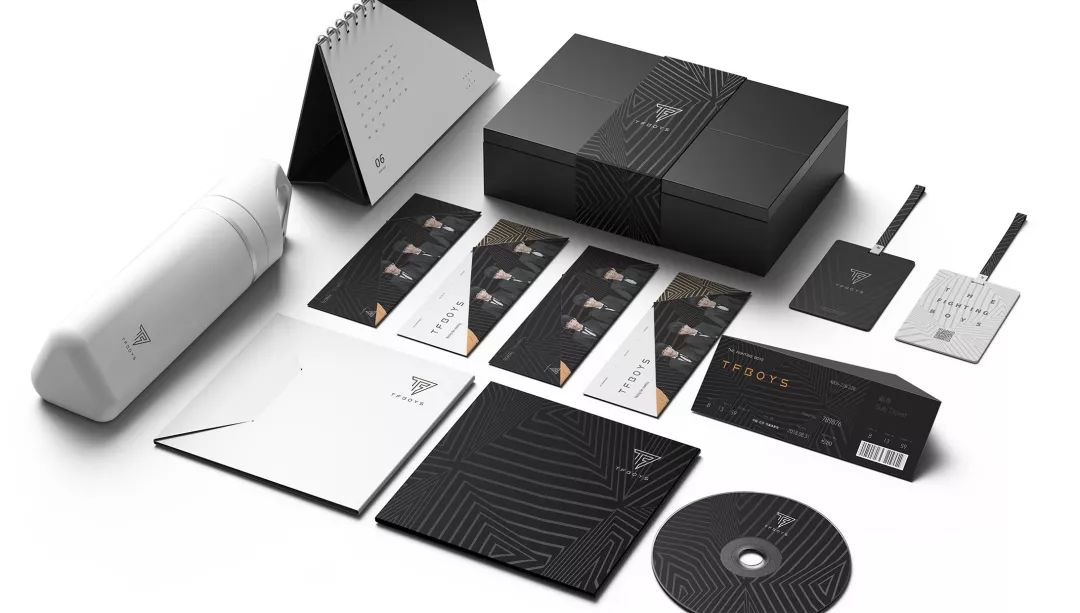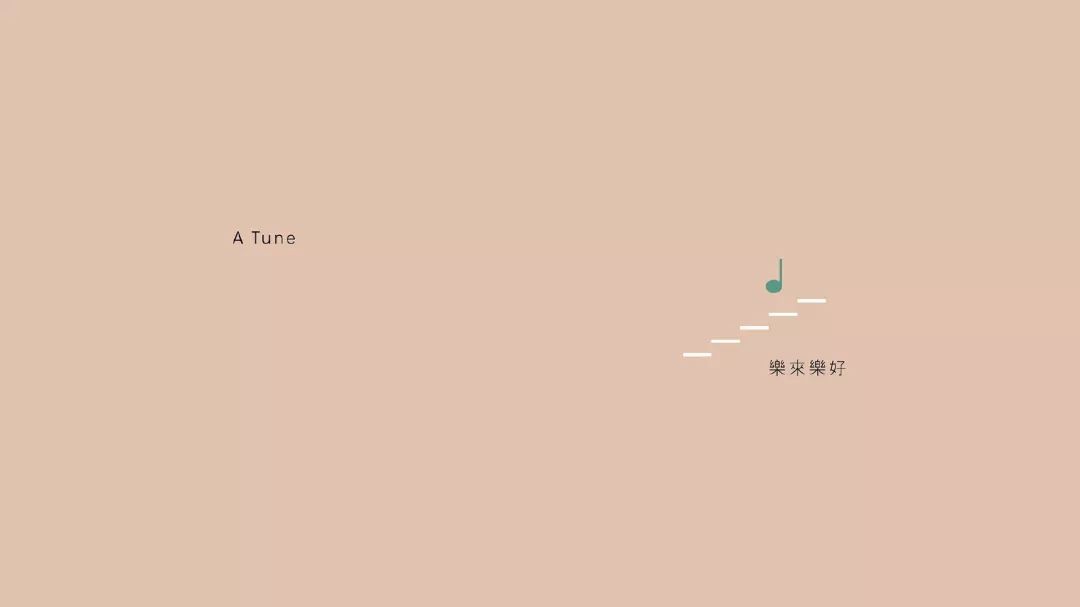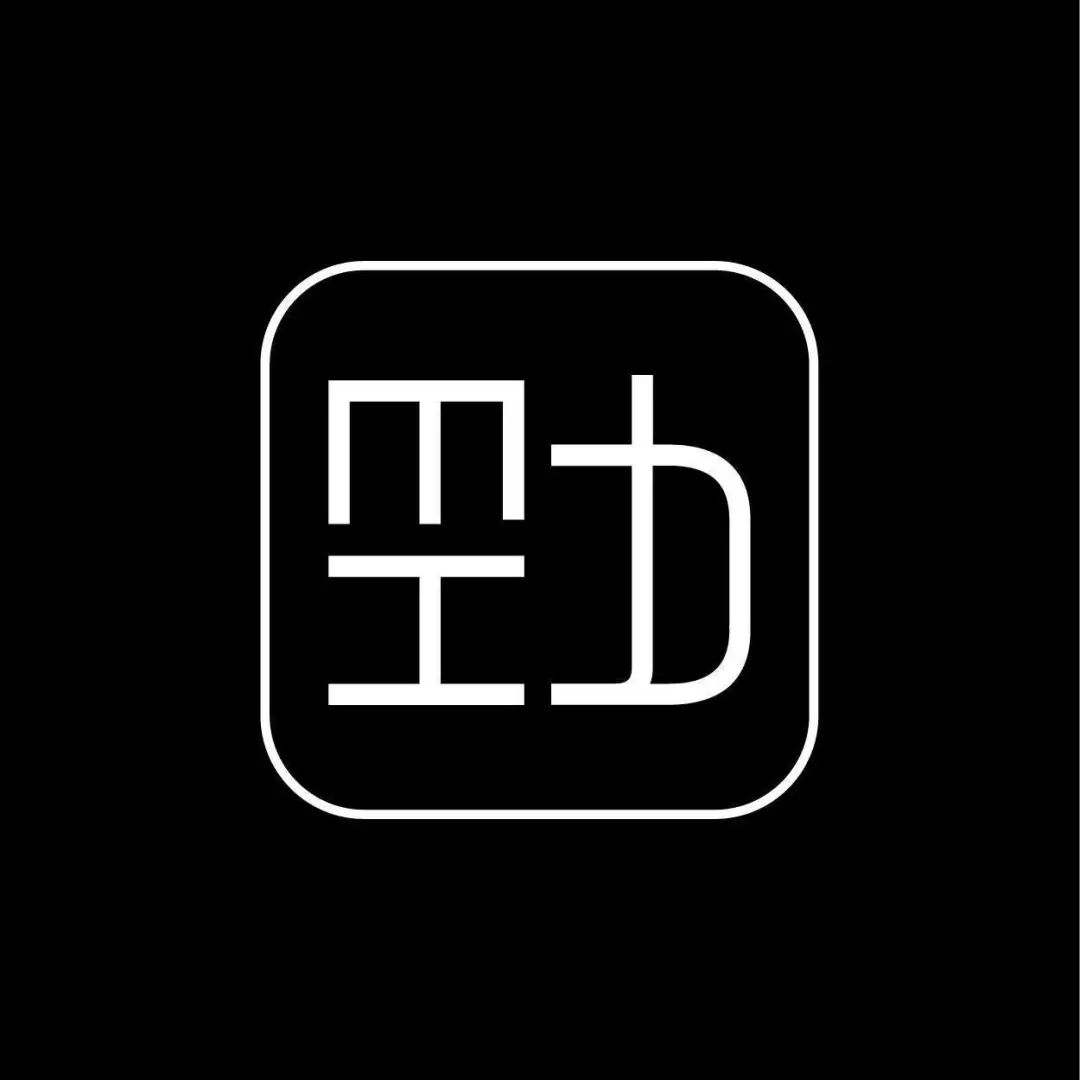
明星的logo什么样?明星的logo设计案例分享
别看有的明星表面上风风光光
背地里却连个logo都拿不出手
很多明星艺人,事业发展到一定程度
会选择成立自己的个人演艺工作室
随之而来的,还有属于自己的Logo
比如女子天团S.H.E的三位成员
在脱离老东家华研娱乐后
就分别宣布成立了自己的公司
作为一名90后
美丫姐上学的时候没少听她们的歌
如今看她们发展的这么好
我也由衷为她们感到高兴
然而从设计师的角度,我还是要说:
这三个人的logo设计也太随便了吧!
首先是Selina的“任真美好有限公司”
年初时,她在ins上晒出了名片和logo
其中这句话
看的我瞬间就懵逼了
logo?超级美腻?在哪呢?
这手上拿的不是张纯色卡片吗?
看了大图才发现,怪不得看不出来
这Logo 也太反人类了!
浅粉色背景+白色细体字
Selina牌色弱自测卡你值得拥有
名片背面的排版也几乎为零
只有两行既没对齐
又偏离了视觉中心的小字
拿到这张名片的朋友
恐怕都是这幅表情
Selina,差设计的钱就说出来
我们给你众筹还不行吗!!
Selina的Logo只是可视度太低
Hebe的就是一次配色车祸现场
大面积低明度低饱和的肉色背景
搭配明度相近的一点点绿色音符
这“要死不活”的配色
还被吐槽上了微博热门
另外,你有没有发现一个问题
这么大一张图,logo的重心在哪?
是这行小字?
还是这个上楼梯的音符?
其实答案是
这些全都是Logo的一部分
整个logo就是这么一长条!
设计师排版的时候是闭着眼的吗
官方竟然真就这样发布了!
哈哈哈哈哈哈哈哈哈哈哈!
松散的排版,沉闷的配色
甚至连粉丝都看不下去了
纷纷主动要求帮做免费设计
这种场面还真是圈内罕见...
相比前两位老板
Ella公司的logo就要正常多了
是“劲桦娱乐”中“劲”字的变形
然而作为一名严谨的设计师
有许多毛病我还是无法忽视
比如边框和文字的粗细不统一
图形与外边框距离不对称等等
除此之外,这个刚劲有力的风格
实在不适合娱乐公司的logo定位
倒是挺适合劲霸男装的
一代女子天团开的公司
logo设计却明显有失水准
实在是令人不解
但其实在娱乐圈
这种Logo跟不上明星身价的情况
还 有 很 多
今天我们就来看一看
那些大牌明星们的个人logo设计
看完你会发现,原来logo做不好
真不光是钱的问题...
1/ 范冰冰
作为曾经的超一线女明星
范冰冰的logo走的精致华丽风
就是比较过时了
这样一个Logo
在20年前做起来还是很费工夫的
如今在X图网却只要几个共享币
就能拥有一大堆同款了
范爷,你早已不是20年前的丫鬟金锁
身价涨了,Logo也是时候换一换了
2/ 林心如
logo想走少女风格可以理解
但不是所有心形元素都叫少女风啊!
运用过度,就是一个非主流的大杂烩
3/ 张翰、明道
两代霸道总裁专业户的logo
都想将总裁气息贯彻到底
却都做出了力不从心的感觉
张翰logo想打造高贵简约的金属风
但这线性渐变也有点太应付了吧...
我觉得要真想打造土豪气质
还不如把爱马仕腰带上的标
抠下来更简单直接
明道的logo则更生动一些
相比之下金属质感也更自然
然而配上背景的妖艳渐变
让它有点像某些夜间消费场所
4/ 王宝强
王宝强的logo是他个人的卡通形象
画风倒是没什么问题
英文名叫”Strong Baby“也没毛病
主要的Bug在于
脑袋怎么少一半!
工作室也是心大,这个残缺的logo
就这样放在了微博首页...
5/ 梁咏琪
梁咏琪的公司logo就厉害了
是著名的logo大师陈幼坚的作品
光听名字你可能不熟悉
但他的作品在你生活中却无处不在
这些家喻户晓的Logo 都出自他手
设计生涯获奖无数,这样一位大神
给梁咏琪设计的logo
按说应该很有气质吧?
然而结果...
香港情歌天后+中国Logo大师
设计出来的Logo怎么这么奇怪?
这漂浮的红色圆圈是什么
为什么有这么重的投影?
难道梁咏琪公司是卖高尔夫球的?
事实上,这只是梁咏琪
“Gmajor娱乐公司”中
小写字母 g 的变形...
看见这个毁容式字体变形
我不由想到了去年日本大阪地铁
(Osaka Metro)的logo改版设计
那个从O到M的巧妙过渡
真是没有对比就没有伤害
纵观这些资历丰富的大牌明星
他们的工作室明明不缺设计预算
logo却总是不尽如人意
究其原因,主要是因为
他们对设计太不重视了
我觉得这些老一辈的艺人们
都严重低估了Logo的影响力
一个有爆点的Logo
能给明星带来意想不到的流量
比如去年火箭少女的logo
引起全网吐槽的同时
也带来了超出预期的讨论度
就是艺人被公司审美坑惨的典型案例
另一个由Logo引爆流量的例子
是从《偶像练习生》节目出道
一个名叫Oner的男团
男团的官方Logo是这样的
而他们发布官方Logo的同时
也公布了它背后的设计过程
简直震惊了半个设计圈:
4个人的男团
logo足足设计了149稿!
(官方发布的全部设计稿)
嫌动图太快可以先看其中一部分
149稿啊...
隔着屏幕都能感受到设计师
从理智到癫狂的过程
这波饱含设计师汗水的营销
的确带来了不小的知名度
让一个刚出道没什么名气的男团
粉丝数在几个月内激增了10倍
对于偶像团体来说
Logo设计尤为重要
所以韩国的当红偶像团体
都有一个特色鲜明的Logo
比如现在最火的TFboys
新粉丝可能会觉得
他们的logo很帅很有型
甚至还斩获了红点设计大奖
及Good Design Award大赛银奖
但实际上只有老粉丝知道
多年前他们刚出道的时候
Logo还是这样的
想象一下,如果他们现在开演唱会
如果还用这个logo的话
会是怎样违和的光景
看完这么多明星的工作室logo
我们不难发现一个有趣的现象
那就是Logo设计已经不单单
代表着一个艺人的形象
而是“设计”本身已经变成了
一种用来引爆话题的营销事件
虽然LOGO的使用方式有点背离初心
但面对这样的甲方
美丫姐只有一句话想说: